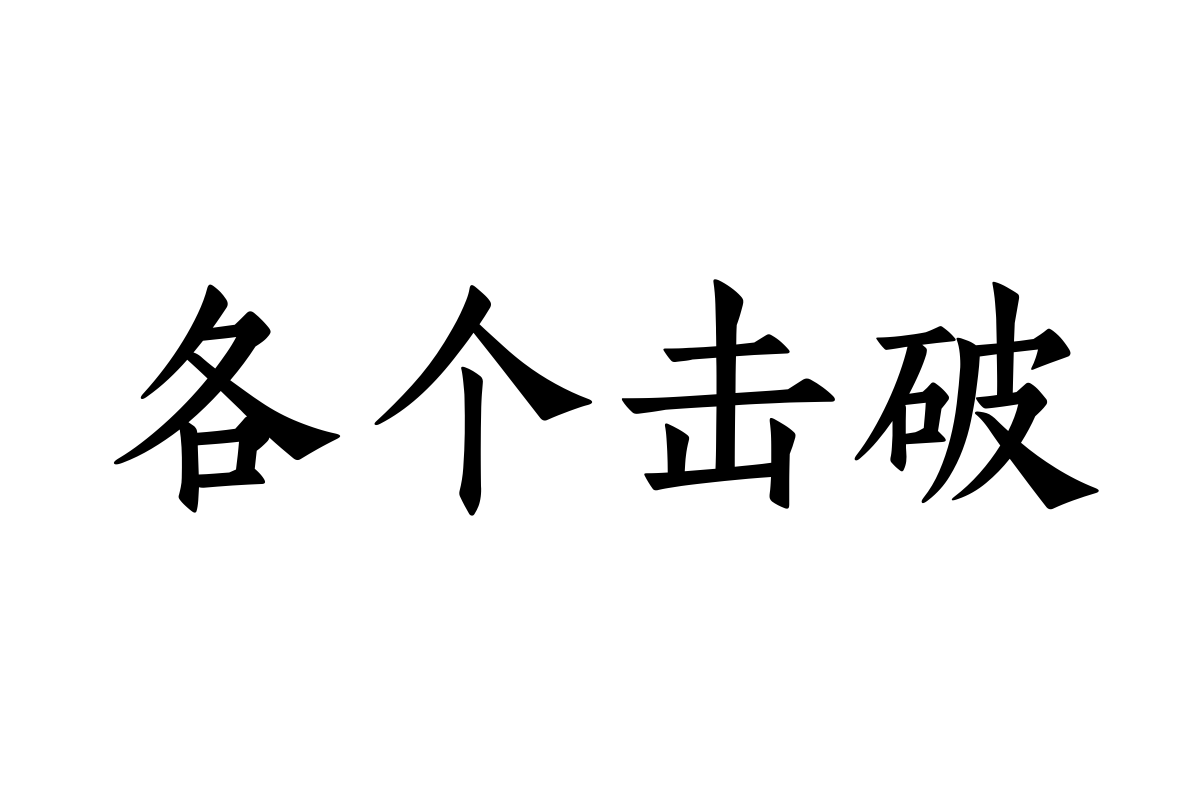
汉仪江南楷宋 W 是一款专为中国书法设计的楷书字体,具有独特的艺术风格和美感。这款字体采用了传统的楷书结构,线条流畅自然,笔画清晰有力。同时,它还融入了一些现代元素,使得字体更加符合现代人的审美需求。
汉仪江南楷宋 W 字体适用于各种需要展示书法风格的应用场景,如广告、包装、书籍封面等。它的使用可以使作品更具艺术感和文化底蕴,提升整体的视觉效果。